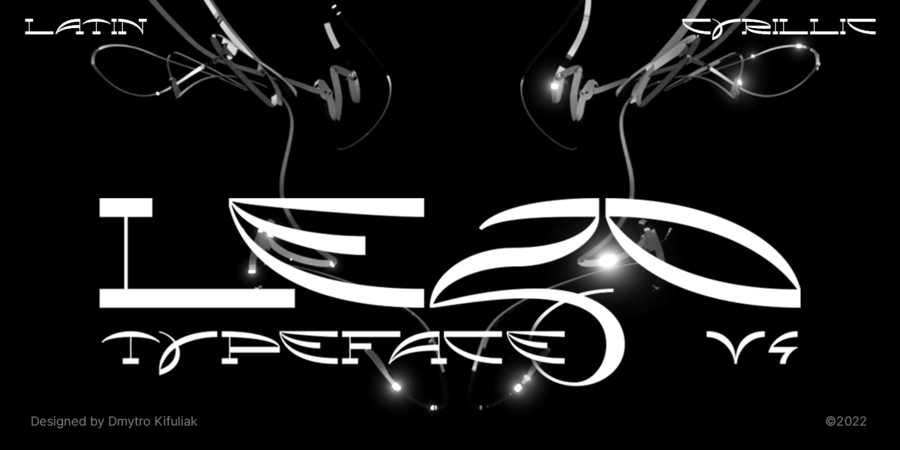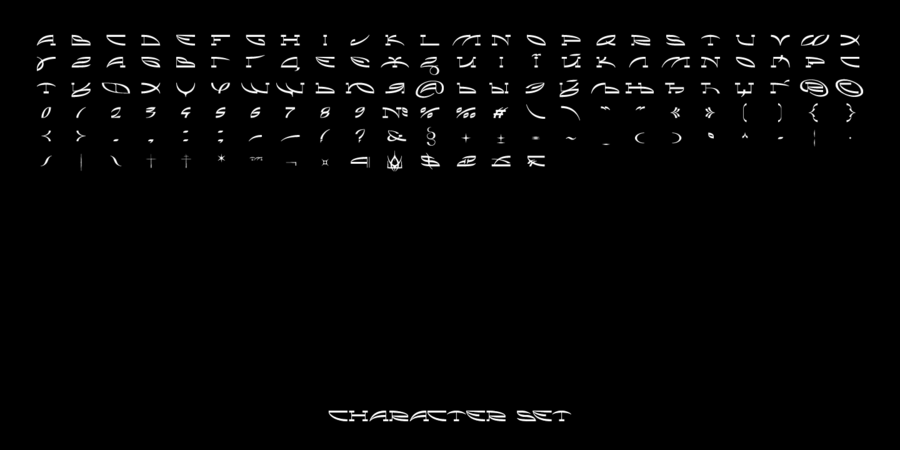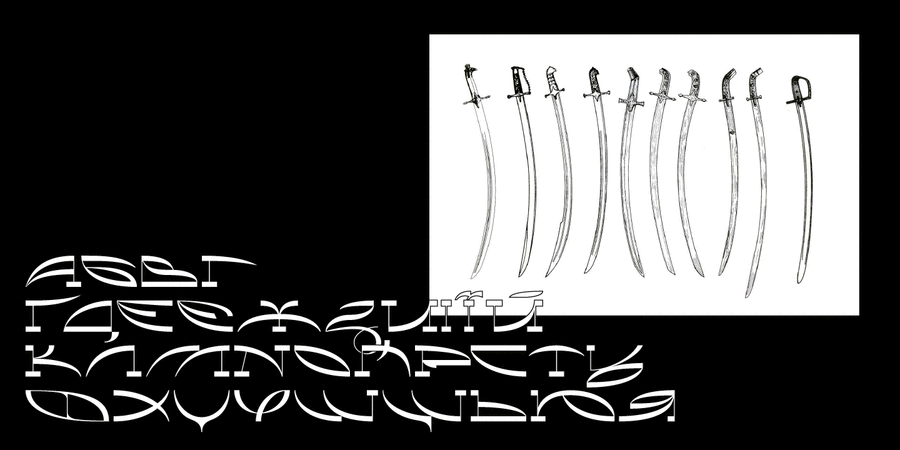
Опис шрифта LezoЛезо – футуристичний акцидентний шрифт з українським характером, натхненний формами мечів XV-XVIII століття. За визначенням, лезо це гостра частина зброї, якою ріжуть, колють або рубають. Метою було створення букв, які стаючи словами прорізають шлях у невідомості. З часом букви почали відточувати свої бездоганні форми і так з'явилося те що ви бачите.
У шрифта високий зворотній контраст, плавні та різкі форми, які створюють між собою унікальний орнамент. Особливістю є використання різноманітних виносних елементів, таких як хвіст в "З","Д","Ц", вони були притаманні історично для українських літер. Цей шрифт показує наскільки цікавою є кирилиця – приємного користування.
Шрифт розробив Дмитро Кіфуляк у 2022 році.